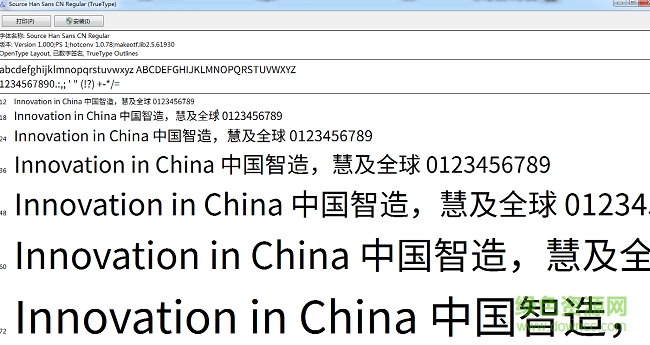
sourcehansanscnregulargbpceuch字體就是一款ttf格式的常規(guī)思源黑體,這款字體我們常常在網(wǎng)上看到,結(jié)構(gòu)嚴謹,粗細一致,易讀性良好,歡迎大家在綠色資源網(wǎng)免費下載!
思源黑體是Adobe與Google歷時三年在2014年7月宣布推出的一款開源字體,完全支持繁體中文、簡體中文、日文和韓文,這些全部都包含在一種字體中。它還包括來自我們頗受歡迎的 Source Sans字體家族的拉丁文、希臘文和西里爾文字形。